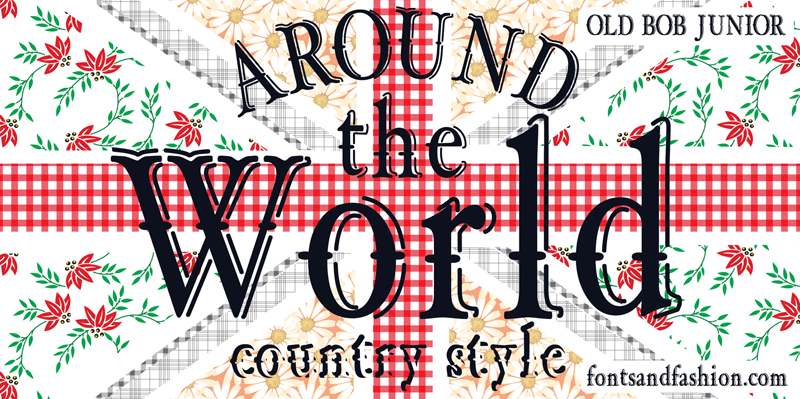
Old Bob Junior font
A Old Bob Junior é uma elegante e vibrante fonte display criada pelo designer Hamilton para aqueles que buscam adicionar personalidade ao seu design visual. Seu estilo atemporal e colorido lhe confere um toque de nostalgia semelhante ao personagem icônico da série animada, tornando-a uma opção perfeita para projetos gráficos criativos ou arquitetônicos. Com linhas leves e cores vivas que lembram os traços vibrantes do Old Bob Junior, a Old Bob Junior é uma fonte de uso instantâneo para qualquer projeto que busque um toque nostálgico sem perder o brilho. Seja para adicionar algum texto em sua página web, criar materiais publicitários ou até mesmo decorar seus livros, essa fonte lhe proporcionará a maneira única que você desejar. A Old Bob Junior é perfeita para aqueles criativos que desejam dar vida ao seu design com uma combinação de modernidade e memória nostálgica, garantindo o destaque em qualquer ambiente visual. Não hesite em explorar mais sobre esta fonte versátil e icônica na nossa biblioteca, onde você encontrará um riquíssimo acervo de recursos gráficos para seu projeto.